Как использовать slab serif в упаковке, вывеске и плакате
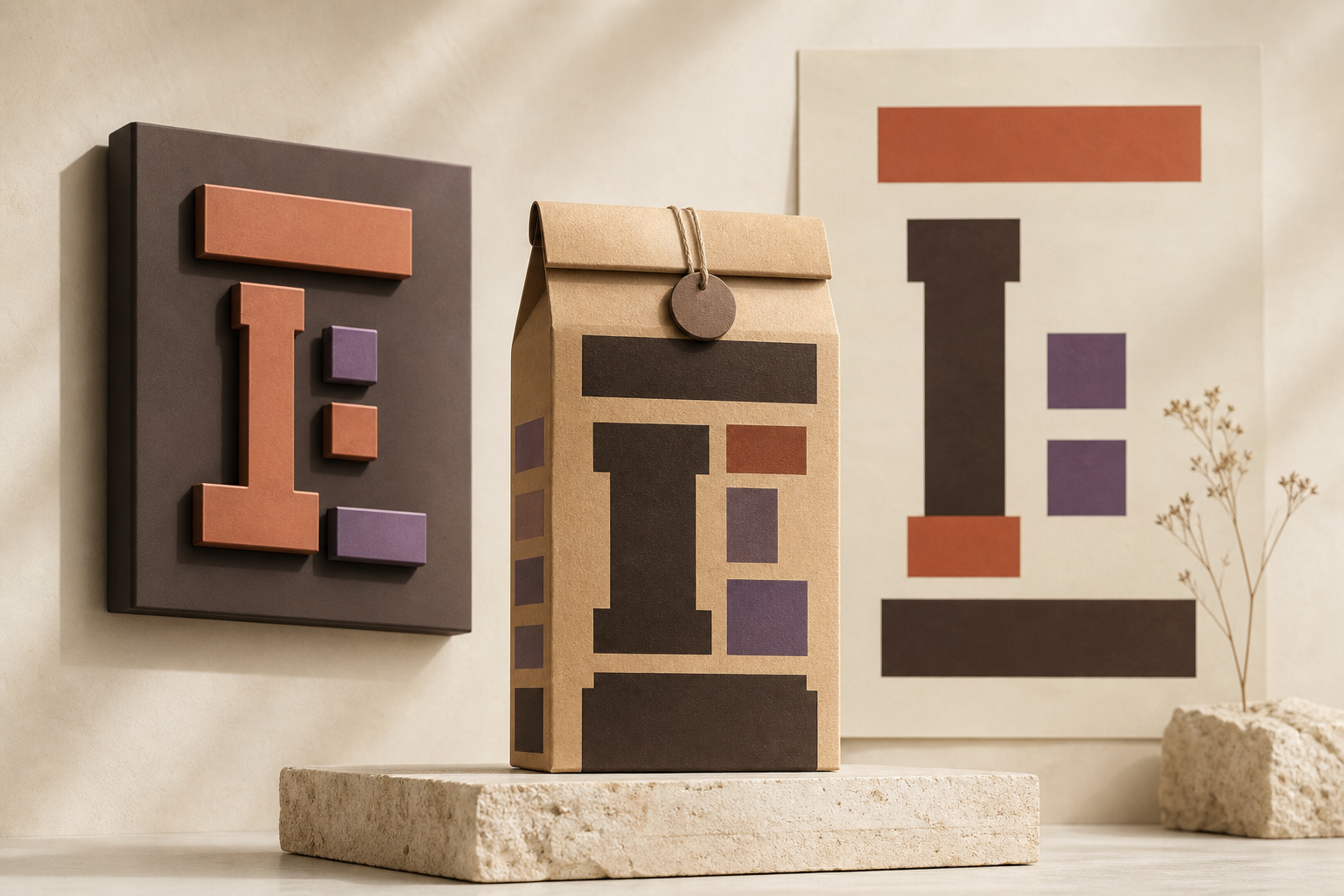
Как использовать slab serif в упаковке, вывеске и плакате
Slab serif лучше всего работает там, где шрифту нужно быстро сообщить о надёжности, силе продукта или характере бренда. Брусковые засечки делают текст заметным на расстоянии и помогают выделить упаковку на полке, вывеску на фасаде или заголовок на рекламном плакате. Ниже разберём выбор гарнитуры, композицию, цвет, масштаб и подготовку макета.
Что такое slab serif и какое впечатление он создаёт
Slab serif — это шрифт с массивными, обычно прямоугольными засечками, которые заметно утолщают окончания штрихов. В русскоязычной типографике такие гарнитуры часто называют брусковыми. По характеру они находятся между традиционными антиквами и более нейтральными гротесками: сохраняют ритм букв с засечками, но выглядят плотнее, жёстче и энергичнее.
Визуальный эффект зависит от конкретной гарнитуры. Контрастная slab serif с тонкими основными штрихами может выглядеть редакционно и элегантно, а тяжёлая моноширинная версия — индустриально и утилитарно. Поэтому нельзя выбирать шрифт только по названию категории: важно оценить форму кириллицы, пропорции, толщину, ширину букв и поведение в нужном размере.
- прочность и устойчивость — уместны для строительных материалов, напитков, инструментов и outdoor-брендов;
- ручную работу и ремесленный характер — полезны для кофеен, пекарен, локальных продуктов и мастерских;
- ретро-настроение — подходит для концепций, связанных с классической рекламой и винтажной упаковкой;
- смелость и прямолинейность — усиливают короткие слоганы, названия коллекций и акционные сообщения.
Как выбрать гарнитуру для конкретного носителя
Один и тот же slab serif не обязан одинаково хорошо работать на коробке, фасаде и плакате. На упаковке шрифт рассматривают в контексте формы, сгибов, этикетки и соседних элементов. Для вывески важны дальность просмотра, освещение и материал изготовления. Для плаката решающими становятся скорость чтения, иерархия сообщений и конкуренция с изображением.
Для упаковки: выразительность без потери информации
На упаковке slab serif особенно эффективен в названии продукта и коротком дескрипторе. Например, для пачки кофе можно использовать плотную гарнитуру в названии «Северный обжарщик», а состав, массу и способ приготовления набрать спокойным гротеском. Такое разделение создаёт фокус: брусковый шрифт формирует характер, а нейтральный текст сохраняет функциональную ясность.
Проверяйте, как буквы ведут себя на реальной развёртке. На узкой боковой грани слишком широкая гарнитура может потребовать неестественного сжатия. На округлой банке строка визуально деформируется из-за поверхности, поэтому название лучше располагать в зоне прямого обзора и не прижимать к краям. Обязательно тестируйте кириллицу, цифры, знаки препинания и сокращения, которые будут в макете.
Для вывески: считывание с расстояния
В вывеске slab serif должен работать как крупная форма, а не как обычный наборный текст. Сначала определите расстояние, с которого человек должен распознать название, затем проверьте высоту букв, межбуквенное расстояние и контраст с фасадом. Сложные декоративные детали, тонкие засечки и тесный кернинг могут исчезнуть при производстве, особенно если вывеска будет вырезаться, окрашиваться или подсвечиваться.
Для магазина фермерских продуктов подойдёт тёплый slab serif с умеренной насыщенностью и открытыми формами кириллических букв. Для мастерской или бара уместна более тяжёлая версия с коротким названием. Если слов много, не пытайтесь решить проблему уменьшением кегля: сократите формулировку, вынесите пояснение на отдельную строку или используйте вторичный гротеск.
Для рекламного плаката: один сильный визуальный акцент
На плакате slab serif хорошо подходит для заголовка, который должен остановить взгляд. Короткая фраза вроде «Городской хлеб» или «Инструмент для дела» получает дополнительный вес благодаря массивным засечкам. Основное правило — не превращать весь макет в демонстрацию одной гарнитуры. Заголовок может быть брусковым, а дата, адрес, условия акции и юридически значимая информация — более нейтральными.
Если изображение насыщенное, используйте slab serif в простой композиции: одну крупную строку, заметный отступ от краёв и достаточное свободное пространство вокруг. Если плакат почти текстовый, можно построить контраст на разных размерах, регистре и плотности, но не стоит одновременно добавлять много цветов, эффектов, рамок и декоративных иллюстраций.
Настройка размера, интерлиньяжа и расстояния между буквами
Массивные засечки меняют восприятие плотности строки. Даже при одинаковом кегле slab serif может казаться крупнее и тяжелее гротеска, поэтому размер выбирают не по числу в программе, а по оптическому масштабу. Сравните несколько вариантов в натуральном размере носителя: этикетку — на распечатанном образце, вывеску — на макете фасада, плакат — с предполагаемой дистанции просмотра.
Плотный заголовок обычно выигрывает от небольшого увеличения межбуквенного расстояния, если буквы начинают слипаться. Но чрезмерный трекинг разрушает цельность слова, особенно у коротких названий. Интерлиньяж должен отделять строки, а не разрывать композицию: в многострочном заголовке полезно сначала выровнять общий силуэт блока, а затем проверить читаемость отдельных букв.
Цвет и контраст в типографике для рекламы
Брусковый шрифт не заменяет контраст. Тёмная надпись на тёмной упаковке, малонасыщенный текст на фактурной бумаге или светлая вывеска рядом с ярким источником света могут потерять читаемость независимо от качества гарнитуры. Оценивайте сочетание текста и фона в реальном контексте, включая материал, фактуру, блики и предполагаемое освещение.
Для ремесленной упаковки можно сочетать тёплый фон, глубокий коричневый и кремовый, но важно оставить заметную разницу по светлоте. Для наружной рекламы часто эффективнее ограниченная палитра из одного акцентного цвета и нейтрального фона. Контур, тень и обводка допустимы только тогда, когда они помогают отделить надпись от фона; декоративный эффект не должен имитировать контраст.
Сочетание slab serif с другими шрифтами
Самый безопасный партнёр для выразительного slab serif — нейтральный гротеск. Он компенсирует тяжесть заголовка и подходит для технических подписей, навигации, состава продукта и контактных данных. В одной композиции достаточно двух гарнитур и ограниченного числа начертаний. Если добавить ещё одну декоративную антикву, визуальные роли могут начать конкурировать.
- отдайте slab serif роль заголовка, названия бренда или короткого слогана;
- используйте гротеск для пояснений, цен, адресов и вторичной информации;
- согласуйте высоту строчных букв, чтобы вторичный текст не выглядел случайно слишком крупным или мелким;
- сравните формы кириллицы в обеих гарнитурах, особенно а, д, ж, к, л и т;
- ограничьте количество акцентов и закрепите одну понятную иерархию.
Три практических сценария применения
Сценарий первый — линейка крафтовых соусов. Название вкуса набирается контрастным slab serif крупно, а цветовая полоса различает варианты: красная для острого, зелёная для травяного, жёлтая для цитрусового. На обороте используется гротеск с более спокойным ритмом. В результате шрифт создаёт ремесленный образ, но не мешает быстро найти нужную информацию.
Сценарий второй — вывеска небольшой ремонтной мастерской. Короткое название набирается тяжёлой брусковой гарнитурой с увеличенным расстоянием между буквами. Под ним размещается компактный дескриптор нейтральным шрифтом. На фасаде оставляют свободное поле вокруг логотипа, чтобы засечки не сливались с облицовкой и надпись не выглядела зажатой.
Сценарий третий — плакат городского фестиваля еды. Slab serif используется для двух слов в заголовке, а крупная цифра даты становится самостоятельным графическим элементом. Остальная информация выстроена в простой вертикальный блок. Такой приём сохраняет эмоциональность плаката и позволяет зрителю быстро ответить на три вопроса: что происходит, когда и где.
- Использовать слишком тяжёлое начертание для длинного текста. Исправление: оставить максимальную насыщенность для коротких заголовков, а пояснения набрать обычным начертанием или гротеском.
- Игнорировать кириллическую версию. Исправление: проверить не только наличие русских букв, но и их рисунок, ширину, высоту и согласованность с латиницей.
- Сжимать буквы по горизонтали, чтобы вместить название. Исправление: выбрать более узкую гарнитуру, сократить формулировку или переработать композицию.
- Проверять макет только на экране. Исправление: сделать пробную печать или визуализацию в масштабе, близком к реальному.
- Применять тень и обводку вместо контраста. Исправление: сначала изменить фон, цвет или размер, а эффекты использовать как вторичный инструмент.
- Заполнять slab serif весь макет. Исправление: создать контраст ролей и оставить шрифту одну главную функцию.
Чеклист перед печатью или производством
- Понятно ли название с первого взгляда и на нужной дистанции?
- Не исчезают ли засечки, просветы и тонкие детали после уменьшения?
- Корректно ли выглядит кириллица, включая кавычки, тире, цифры и знаки процента?
- Сохраняется ли контраст при выбранном материале, фактуре и освещении?
- Есть ли достаточный отступ от сгибов, краёв, креплений и соседних объектов?
- Согласованы ли заголовок, вторичный текст и служебная информация по иерархии?
- Проверены ли вылеты, векторизация, цветовой профиль и требования производства?
- Работает ли макет без декоративных эффектов, если их отключить?
Подходит ли slab serif для маленькой этикетки?
Да, но преимущественно для короткого названия или отдельного акцента. На маленькой этикетке массивные засечки могут визуально закрывать просветы между буквами, поэтому нужно тестировать реальный размер, бумагу и способ печати. Основной информационный текст часто лучше оставить более нейтральным и открытым.
Можно ли использовать один slab serif для бренда и рекламы?
Можно, если гарнитура имеет достаточно начертаний и хорошо поддерживает кириллицу. Для логотипа потребуется индивидуальная настройка формы, а для рекламных сообщений — понятная система размеров и отступов. Необязательно набирать этой гарнитурой каждую строку: узнаваемость бренда поддерживается повторением ключевой роли шрифта.
Чем slab serif отличается от обычной антиквы?
Slab serif обычно отличается более массивными и прямыми засечками, меньшим или умеренным контрастом штрихов и более плотным визуальным характером. Традиционная антиква чаще воспринимается как книжная, классическая или редакционная. Граница между категориями бывает условной, поэтому при выборе важнее конкретный рисунок гарнитуры и задача макета.
Какой цвет лучше выбрать для брускового шрифта?
Универсального цвета нет: его выбирают относительно фона, материала и характера бренда. Тёмный текст на светлом фоне обычно легче контролировать, но яркий цвет тоже работает при достаточном контрасте. Для вывески дополнительно учитывают подсветку, блики и изменение восприятия оттенка днём и вечером.
Нужно ли сочетать slab serif с гротеском?
Это не обязательное требование, но гротеск часто помогает выстроить ясную иерархию. Slab serif берёт на себя эмоциональный заголовок, а гротеск — пояснения, навигацию и технические сведения. Если вся композиция короткая, достаточно одной гарнитуры с разными начертаниями и размерами.
Можно ли использовать slab serif для световой вывески?
Да, если конструкция сохраняет форму засечек и просветов в выбранном масштабе. Перед производством проверьте макет в контурном виде, учтите толщину материала, расстояние между элементами и способ подсветки. Слишком тонкие детали могут потеряться, а чрезмерно плотные буквы — слиться в световое пятно.